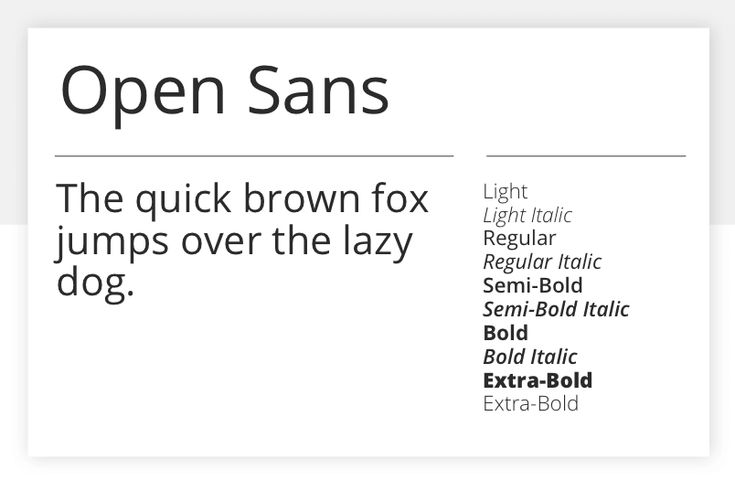
25 самых популярных шрифтов Google — 2020 | by Masterpicks
25 Самые популярные шрифты Google — Google Fonts — это огромный бесплатный каталог избранных шрифтов с открытым исходным кодом, созданный командой Google и разработанный разработчиками шрифтов, дизайнерами и агентствами по всему миру. Он был основан в 2010 году. С тех пор он регулярно обновляется и на момент написания этой статьи насчитывает 980 шрифтов.
В этой статье мы собрали 25 самых популярных шрифтов Google на февраль 2020 года
Робот Кристиан Робертсон
Робот имеет двойственную природу. У него механический скелет, а формы в основном геометрические. В то же время шрифт отличается дружелюбными и открытыми изгибами. В то время как некоторые гротески искажают форму букв, чтобы добиться жесткого ритма, Roboto не идет на компромиссы, позволяя буквам принимать их естественную ширину.
Это обеспечивает более естественный ритм чтения, более характерный для гуманистических шрифтов и шрифтов с засечками.
Open Sans — гуманистический шрифт без засечек, разработанный Стивом Маттесоном, директором шрифтов Ascender Corp. Эта версия содержит полные 897 наборов символов, который включает стандартные наборы символов ISO Latin 1, Latin CE, греческий и кириллицу. Open Sans был разработан с вертикальным акцентом, открытыми формами и нейтральным, но дружелюбным внешним видом. Он был оптимизирован для печати, Интернета и мобильных интерфейсов и имеет отличные характеристики разборчивости букв.
Лато от Лукаша Дзеджича
Работая над Лато, Лукаш пытался тщательно сбалансировать некоторые потенциально конфликтующие приоритеты. Он хотел создать шрифт, который казался бы довольно «прозрачным» при использовании в основном тексте, но отображал бы некоторые оригинальные черты при использовании в больших размерах. Он использовал классические пропорции (особенно заметные в верхнем регистре), чтобы придать формам букв знакомую гармонию и элегантность.
В то же время он создал гладкий шрифт без засечек, который делает очевидным тот факт, что Lato был разработан в 2010 году, хотя он не соответствует какой-либо современной тенденции.
Полукруглые детали букв придают Lato ощущение тепла, а прочная структура обеспечивает стабильность и серьезность. «Мужчина и женщина, серьезные, но дружелюбные. С ощущением лета», — говорит Лукаш.
Oswald Вернона Адамса
Oswald — это переработка классического стиля, исторически представленного шрифтами без засечек «Альтернативная готика». Персонажи Освальда изначально были перерисованы и преобразованы, чтобы лучше соответствовать пиксельной сетке стандартных цифровых экранов. Oswald предназначен для свободного использования в Интернете веб-браузерами на настольных компьютерах, ноутбуках и мобильных устройствах.
Робото имеет двойственную природу. У него механический скелет, а формы в основном геометрические. В то же время шрифт отличается дружелюбными и открытыми изгибами.
В то время как некоторые гротески искажают форму букв, чтобы добиться жесткого ритма, Roboto не идет на компромиссы, позволяя буквам принимать их естественную ширину. Это обеспечивает более естественный ритм чтения, более характерный для гуманистических шрифтов и шрифтов с засечками.
Slabo 27px от John Hudson
Slabo — это набор шрифтов определенного размера для использования в онлайн-рекламе и других целях в Интернете. В настоящее время коллекция включает этот шрифт, Slabo 27px и Slabo 13px. Каждый шрифт в коллекции точно настроен для использования с размером пикселя в его названии.
Montserrat by Julieta Ulanovsky
Старые плакаты и вывески в традиционном районе Montserrat в Буэнос-Айресе вдохновили Джульетту Улановски на разработку этого шрифта и спасение красоты городской типографики, появившейся в первой половине двадцатого века. По мере того, как городское развитие меняет это место, оно никогда не вернется к своей первоначальной форме и навсегда потеряет такие особенные и уникальные замыслы.
В буквах, вдохновивших этот проект, есть работа, самоотверженность, забота, цвет, контраст, свет и жизнь, день и ночь! Это те типы, которые делают город таким красивым. Проект Монтсеррат начался с идеи спасти то, что находится в Монтсеррате, и освободить его под свободной лицензией SIL Open Font License.
Source® Sans Pro, первое семейство шрифтов Adobe с открытым исходным кодом, разработанное Полом Д. Хантом. Это шрифт без засечек, предназначенный для использования в пользовательских интерфейсах.
Raleway от Multiple Designers
Raleway — это элегантное семейство шрифтов без засечек, предназначенное для заголовков и других шрифтов большого размера. Первоначально разработанный Мэттом Макинерни как один тонкий груз, он был расширен до семейства из 9 весов Пабло Импаллари и Родриго Фуэнзалида в 2012 году и iKerned Иджино Марини.
PT Sans разработан для проекта «Публичные шрифты Российской Федерации». Также доступно второе семейство проекта, PT Serif.
Open Sans — гуманистический шрифт без засечек, разработанный Стивом Маттесоном, директором по шрифтам Ascender Corp.
Эта версия содержит полный набор символов 897, включая стандартные наборы символов ISO Latin 1, Latin CE, греческий и кириллицу. Open Sans был разработан с вертикальным акцентом, открытыми формами и нейтральным, но дружелюбным внешним видом. Он был оптимизирован для печати, Интернета и мобильных интерфейсов и имеет отличные характеристики разборчивости букв.
Roboto Slab Кристиан Робертсон
Roboto имеет двойную природу. У него механический скелет, а формы в основном геометрические. В то же время шрифт отличается дружелюбными и открытыми изгибами. В то время как некоторые гротески искажают форму букв, чтобы добиться жесткого ритма, Roboto не идет на компромиссы, позволяя буквам принимать их естественную ширину. Это обеспечивает более естественный ритм чтения, более характерный для гуманистических шрифтов и шрифтов с засечками.
Merriweather был разработан, чтобы быть текстовым шрифтом, который приятно читать на экране. Он имеет очень большую высоту x, слегка сжатые формы букв, мягкое диагональное напряжение, прочные засечки и открытые формы.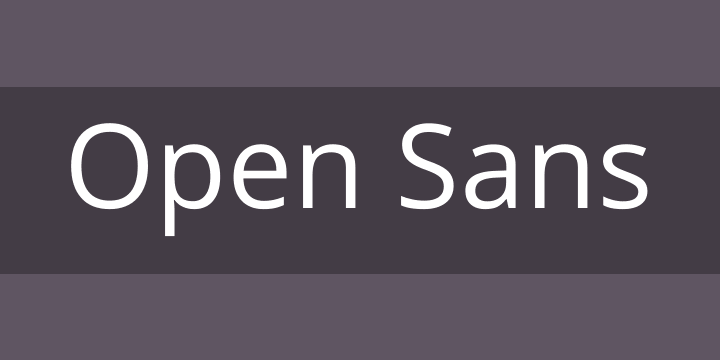
Lora от Cyreal
Lora — это хорошо сбалансированный современный шрифт с засечками, уходящий своими корнями в каллиграфию. Это текстовый шрифт с умеренной контрастностью, хорошо подходящий для основного текста.
Ubuntu от Далтона Маага
Новое семейство шрифтов Ubuntu было запущено, чтобы личность Ubuntu можно было увидеть и почувствовать в каждом меню, кнопке и диалоговом окне. Шрифт без засечек, использует функции OpenType и хинтуется вручную для ясности на экранах настольных компьютеров и мобильных компьютеров.
Noto помогает сделать Интернет более красивым на всех платформах для всех языков. В настоящее время Noto охватывает более 30 скриптов, а в будущем будет охватывать весь Unicode. Это семейство Sans Latin, Greek и Cyrillic. Он имеет стили Regular, Bold, Italic и Bold Italic и намекает. Он является производным от Droid и, как и Droid, имеет сестринское семейство с засечками, Noto Serif.
Этот дизайн подходит для этого периода, и, хотя он не является возрождением какого-либо конкретного дизайна, на него повлияли проекты Джона Баскервиля и дизайны «шотландских римлян».
Будучи дисплеем (большого размера) в переходном жанре, функционально и стилистически он может сопровождать Грузию для основного текста.
Poppins от Indian Type Foundry
Геометрические шрифты без засечек стали популярным инструментом дизайна с тех пор, как эти актеры вышли на мировую сцену. Поппинс — один из новичков в этой давней традиции. Благодаря поддержке систем письма деванагари и латиницы, это интернациональный подход к жанру.
PT Sans основан на русских шрифтах без засечек второй половины ХХ века, но в то же время имеет отличительные черты современного гуманистического дизайна. Семейство состоит из 8 начертаний: 4 основных начертания, 2 начертания для небольших размеров и 2 узких начертания для экономичного набора.
PT Serif — переходный шрифт с засечками и гуманистическими окончаниями. Он предназначен для использования вместе с PT Sans и гармонизирован по показателям, пропорциям, весу и дизайну.
Arimo от Стива Маттесона
Arimo был разработан Стивом Маттесоном как инновационный, освежающий дизайн без засечек, который метрически совместим с Arial™.
Arimo предлагает улучшенные характеристики читаемости на экране и общеевропейский набор символов WGL, а также удовлетворяет потребности разработчиков, которым нужны совместимые по ширине шрифты для обеспечения переносимости документов между платформами.
Roboto Mono от Кристиана Робертсона
Roboto Mono — моноширинное дополнение к семейству шрифтов Roboto. Как и другие члены семейства Roboto, шрифты оптимизированы для удобочитаемости на экранах самых разных устройств и в различных средах чтения. В то время как моноширинная версия связана со своим двоюродным братом с переменной шириной, она без колебаний меняет формы, чтобы лучше соответствовать ограничениям моноширинной среды. Например, к узким глифам, таким как «I», «l» и «i», добавлены засечки для более ровной текстуры, а более широкие глифы скорректированы для веса. Изогнутые крышки, такие как «C» и «O», имеют более прямые стороны от Roboto Condensed.
Titillium родился в Accademia di Belle Arti di Urbino как дидактический проект Курс Типовой дизайн Мастера визуального дизайна Кампи Визиви.